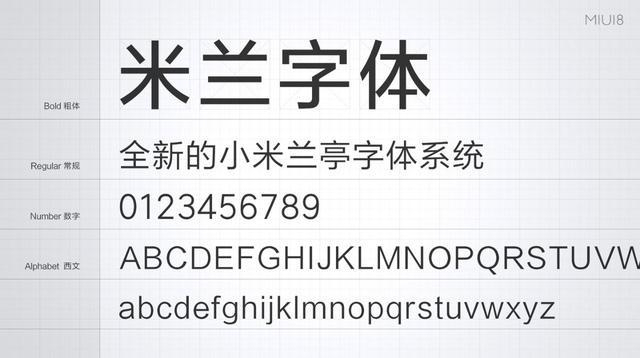
今天咱们来看看,手机畅销全球的小米公司出品过的字体!
小米
字体名称:小米兰亭
「小米兰亭」字体从 6763 个常用汉字、标点符号、拉丁字母,扩展到 27533 个汉字的全字库,号称「重新定义了小米手机的中文移动阅读体验」。2016 年 5 月 10 日,该字体在小米 MAX 大屏手机的发布会上被重点介绍。同时,小米强调自己是「除了苹果、谷歌之外,全球第三家定制移动端中文阅读字体的厂商」
小米官方联合方正推出的一款字体,主要适用于小米手机,对于大段文字来说,阅读体验很好,我觉得跟微软雅黑 Light 比较相似:
在 PPT 制作中,使用这款字体的话,呈现效果也不错,很简洁:
小米自从有了自己家的字体后,发布会上全部采用了自己字体,即预防了侵权的风险,同时也彰显了品牌的实力,一举两得,咱们可以看下这款字体用在PPT中的效果,还是很赞的哦:
整体感觉好像还不错,有种很浓郁的中国风的美感,相信用在我们的PPT中,也会让PPT变得精致!怪不得号称雷军喜欢的字体: